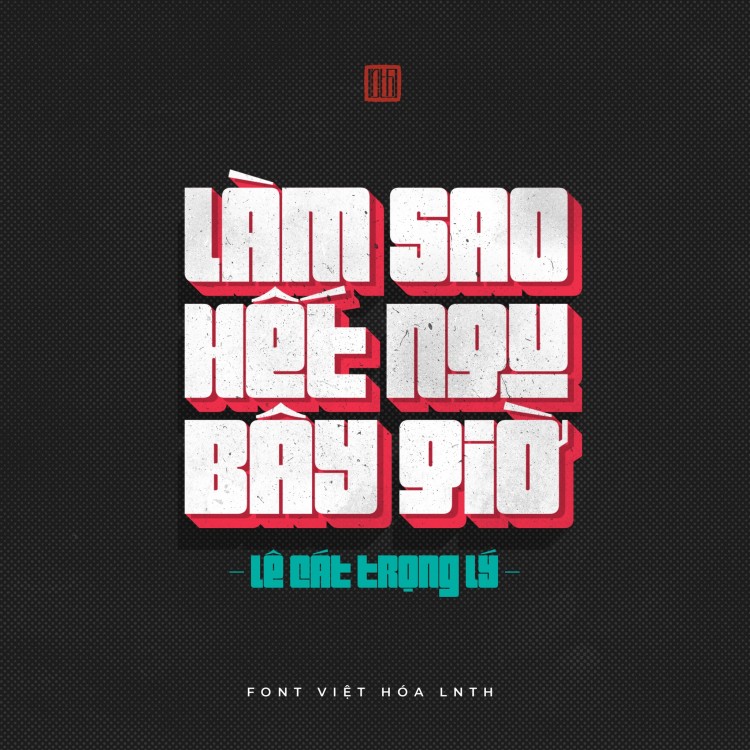
Font việt hóa LNTH Pincoya Black
Font việt hóa LNTH Pincoya Black – Bộ font chữ thiết kế độc đáo và mạnh mẽ
Giới thiệu về Font việt hóa LNTH Pincoya Black
Trong thế giới thiết kế đồ họa hiện đại, việc lựa chọn một bộ Font Miễn Phí chất lượng luôn là ưu tiên hàng đầu của các designer. Font việt hóa LNTH Pincoya Black nổi lên như một hiện tượng nhờ phong cách thiết kế đậm chất Latin, mang lại cảm giác phóng khoáng nhưng không kém phần chắc chắn. Đây là sản phẩm được lấy cảm hứng từ những nét chữ vẽ tay trên bảng hiệu tại các quốc gia Nam Mỹ, tạo nên một diện mạo đầy cá tính cho mọi tác phẩm nghệ thuật. Phiên bản việt hóa bởi LNTH đã giúp người dùng Việt dễ dàng tiếp cận và sử dụng trong các dự án đòi hỏi tính bản địa hóa cao.
Đặc điểm nổi bật của LNTH Pincoya Black
Đặc trưng lớn nhất của Font việt hóa LNTH Pincoya Black chính là độ dày của nét chữ. Các con chữ được xây dựng với khối hình học vững chãi, các góc bo tròn mềm mại tạo nên sự cân bằng hoàn hảo giữa sức mạnh và sự tinh tế. Với bảng mã ký tự đầy đủ dấu tiếng Việt, người dùng không còn lo lắng về lỗi font khi soạn thảo văn bản hay làm tiêu đề. Bộ chữ này cực kỳ phù hợp cho các thiết kế poster, bìa sách, hoặc các ấn phẩm truyền thông dành cho học sinh và sinh viên nhờ vẻ ngoài trẻ trung và hiện đại.
Ứng dụng thực tế của Font việt hóa LNTH Pincoya Black
Sự linh hoạt là điểm cộng lớn khiến Font việt hóa LNTH Pincoya Black được yêu thích rộng rãi. Trong môi trường học đường, các thầy cô giáo hoặc các em học sinh có thể sử dụng font chữ này để trang trí báo tường, làm slide thuyết trình sinh động hoặc thiết kế thiệp mời cho các sự kiện của lớp. Đối với lĩnh vực quảng cáo, font chữ này phát huy tác dụng tối đa khi xuất hiện trên các bảng hiệu hoặc logo thương hiệu cần sự phá cách. Khả năng hiển thị tốt trên cả nền tảng in ấn và kỹ thuật số giúp nội dung của bạn luôn nổi bật và thu hút sự chú ý của người xem ngay từ cái nhìn đầu tiên.
Lưu ý khi sử dụng trong thiết kế đồ họa
Mặc dù Font việt hóa LNTH Pincoya Black rất ấn tượng, nhưng bạn cần biết cách phối hợp màu sắc để tăng hiệu quả thị giác. Do tính chất là dòng chữ Black (siêu đậm), bạn nên ưu tiên sử dụng các màu sắc tương phản mạnh giữa chữ và nền. Chẳng hạn, chữ vàng trên nền đen hoặc chữ trắng trên nền xanh đậm sẽ tạo nên một tổng thể vô cùng hài hòa. Ngoài ra, hãy hạn chế sử dụng bộ font này cho các đoạn văn bản dài vì độ dày lớn có thể gây mỏi mắt cho người đọc. Thay vào đó, hãy biến nó thành tâm điểm của những câu khẩu hiệu hoặc tiêu đề chính trong dự án của mình.
Kết luận về bộ Font việt hóa LNTH Pincoya Black